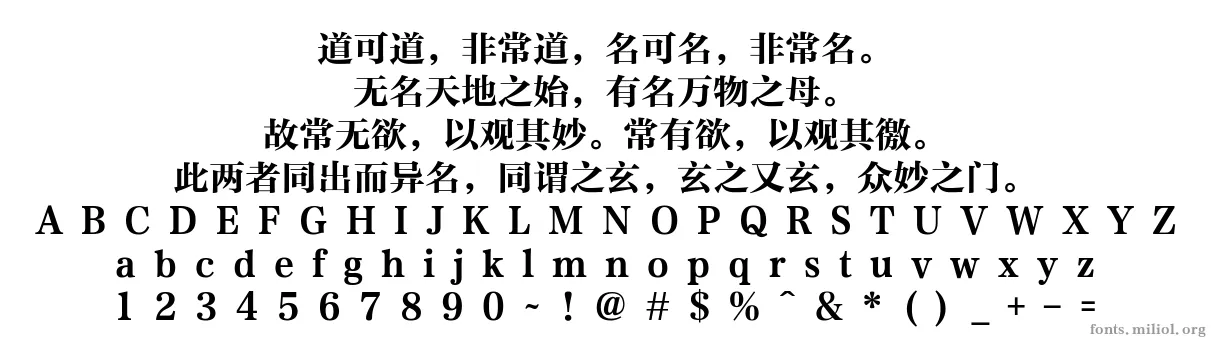
方正粗雅宋_GBK (FYaSong-B-GBK) (FZCYSK--GBK1-0) 字体下载
《方正粗雅宋_GBK:传统与现代交融的字体美学》
方正粗雅宋_GBK(FYaSong-B-GBK)是一款兼具传统宋体韵味与现代设计美学的经典字体。作为方正字库的重要成员,它以GBK编码标准为基础,支持多达两万余个汉字字符,广泛适用于印刷出版、平面设计及数字化排版领域。其笔划粗壮有力,横平竖直间保留了宋体的典雅气质,同时通过优化转折与收笔细节,赋予文字更强的视觉张力和辨识度。
在设计上,方正粗雅宋_GBK继承了宋体“横细竖粗”的核心特征,但通过加粗处理强化了整体稳重感,特别适合标题、广告语等需要突出表现力的场景。字体的结构严谨,比例协调,既符合中文书写规范,又能适应多平台显示需求。无论是传统书籍装帧还是现代屏幕阅读,均能呈现清晰而富有文化底蕴的视觉效果。
方正粗雅宋_GBK 字体映射图